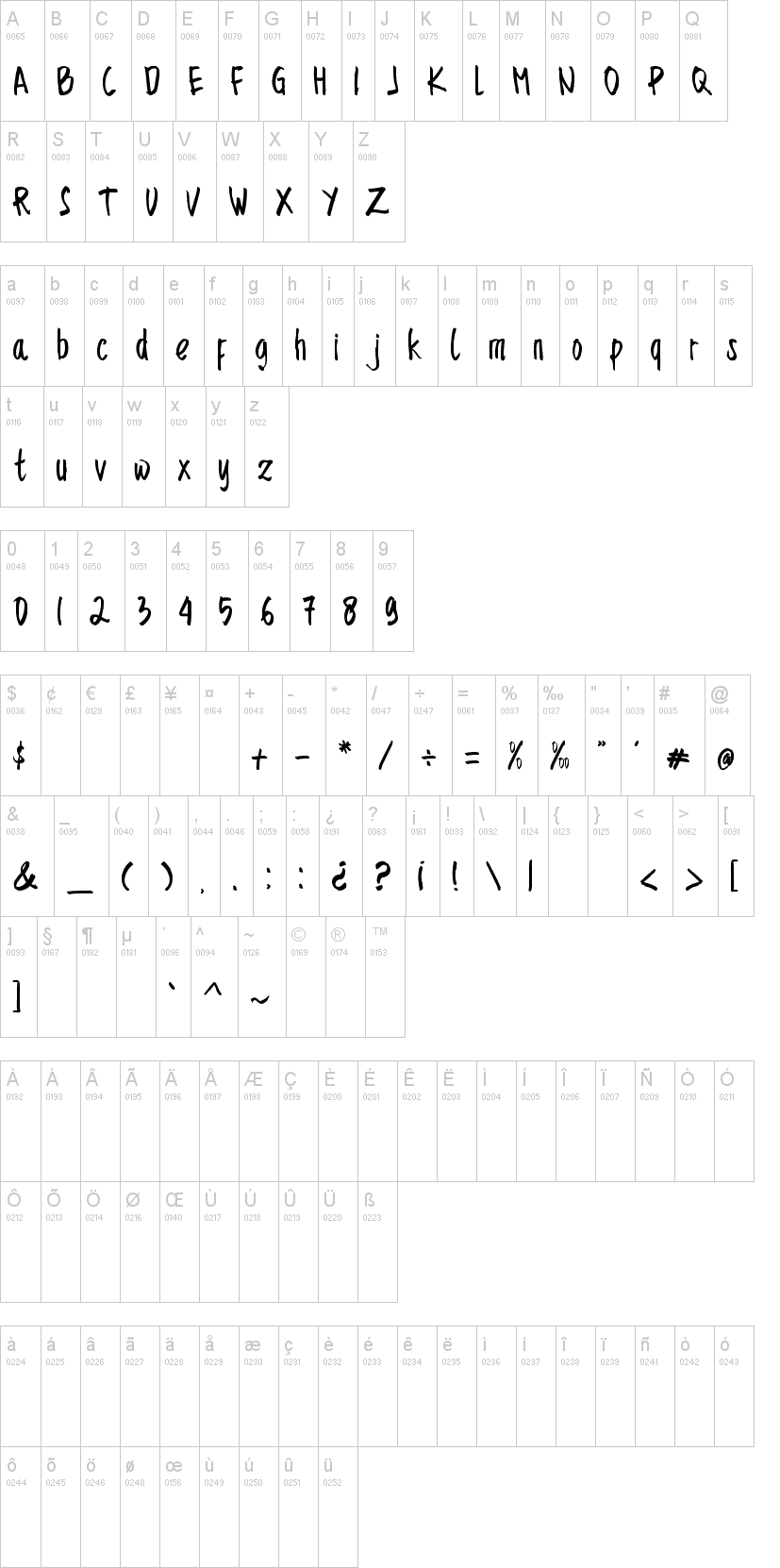
Sencillo Handdrawn
Sencillo Handdrawn 字体是一款手绘风格的字体,非常适合用于设计卡片、海报、宣传单、书籍封面等等,让你的设计更有个性和艺术感。 这款字体的字形流畅自然,仿佛是由一支笔或者一支画笔手绘而成。每个字母都充满了细节和纹理,让你的设计作品更加生动和有趣。字体有两种风格可供选择,一种是填充式的,另一种是线框式的。 Sencillo Handdrawn 字体支持多种语言,包括英文、西班牙文、法文等等,因此非常适合用于国际性的设计作品。 总的来说,Sencillo Handdrawn 字体是一款非常优秀的手绘字体,适用于多种设计场景,如果你正在寻找一款富有个性和创意的字体,那么它绝对值得一试。
Sencillo Handdrawn是一款非常不错的手写艺术字体,具有很好的视觉感,适合于文化类的宣传设计、商业类品牌的广告和产品包装设计以及个性化文字排版等较多场景。